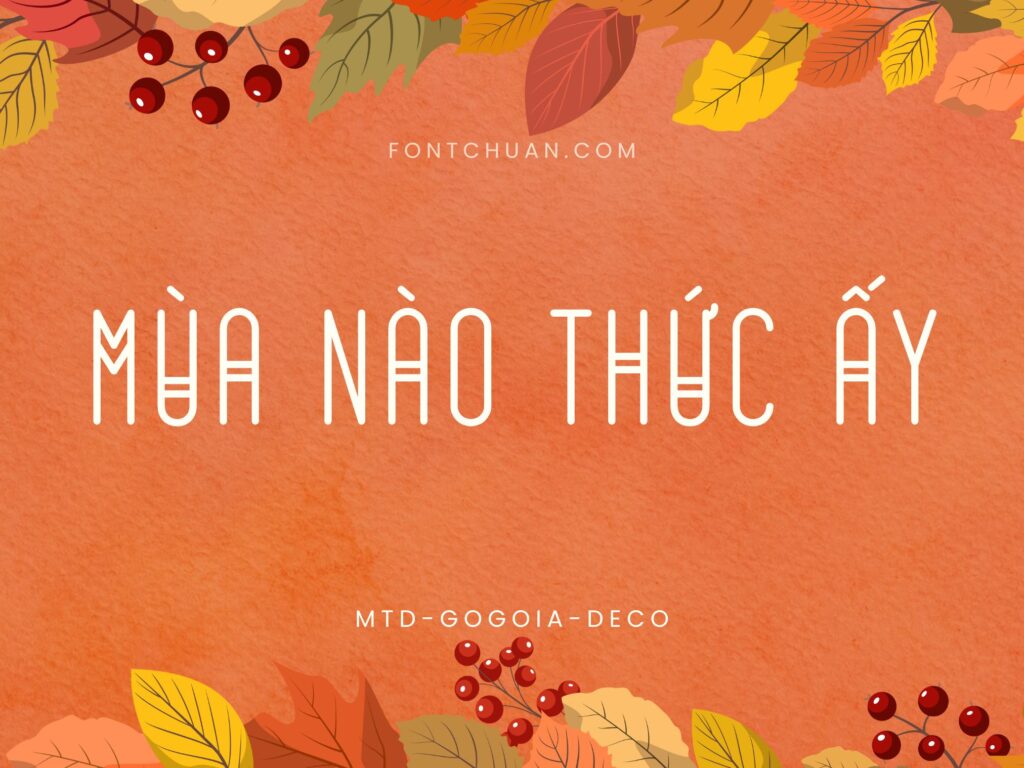
Font MTD Gogoia Deco Việt Hóa
Font MTD Gogoia Deco là một kiểu chữ trang trí mang phong cách Art Deco, được thiết kế bởi Alan de Sousa và Việt hóa bởi Mộc Hạ. Font này hỗ trợ đầy đủ tiếng Việt cùng hơn 90 ngôn ngữ khác, mở rộng khả năng ứng dụng trong các thiết kế đa ngôn ngữ. Đây là một trong những phông chữ được cộng đồng thiết kế đánh giá cao và sử dụng trong nhiều dự án sáng tạo, đáp ứng nhu cầu đa dạng của người dùng.
MTD Gogoia Deco nổi bật với các đường nét hình học và trang trí độc đáo, mang đến cảm giác hiện đại và sang trọng. Font rất phù hợp cho các thiết kế logo, tiêu đề, bao bì sản phẩm, thiệp mời và các ấn phẩm đòi hỏi sự tinh tế và nghệ thuật. Các ngành nghề phù hợp bao gồm quảng cáo, giáo dục, công nghệ, thiệp cưới và ảnh cưới. Font này cũng lý tưởng cho các sự kiện như Tết, Giáng sinh, Valentine và các lễ hội khác.